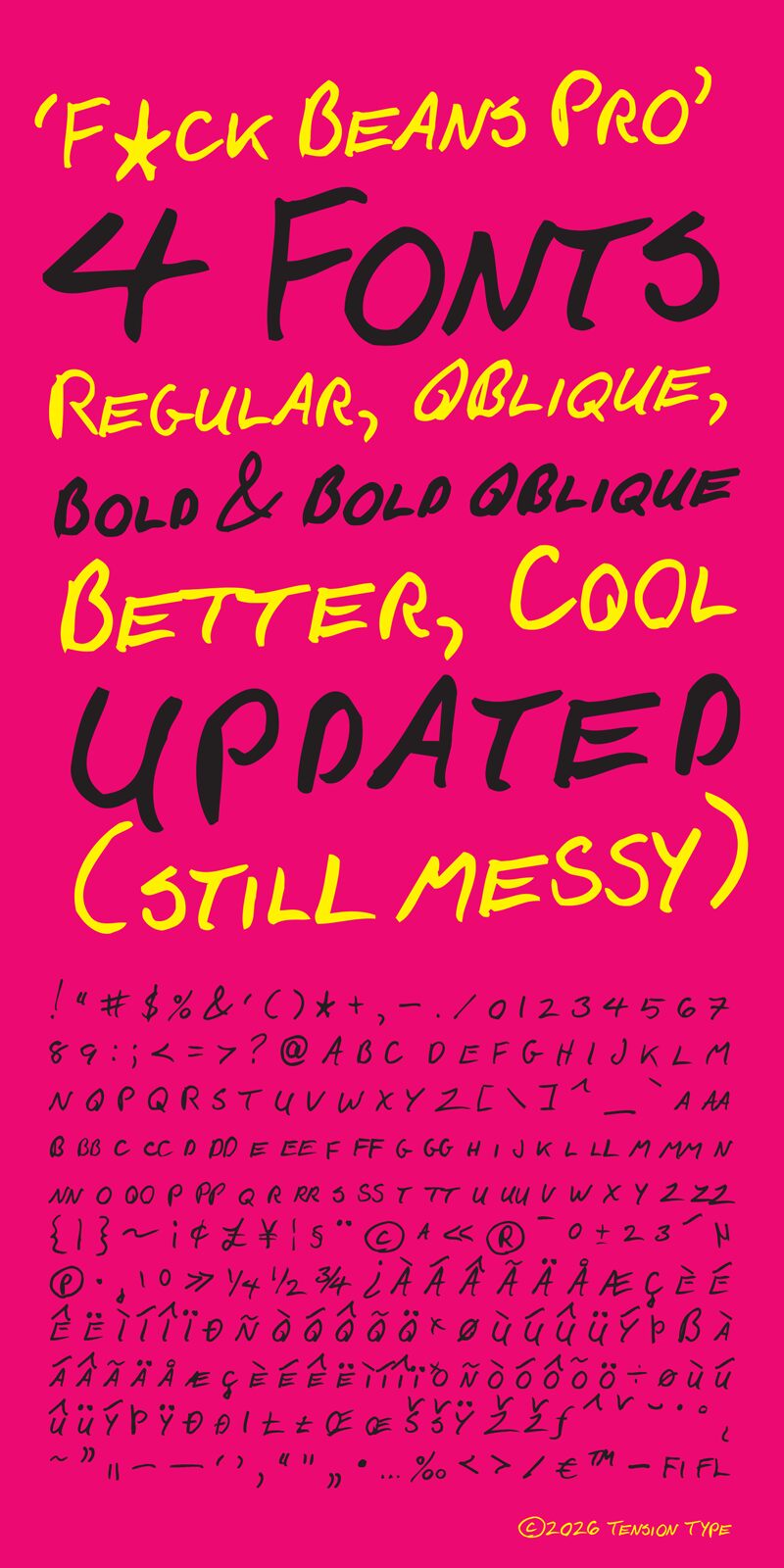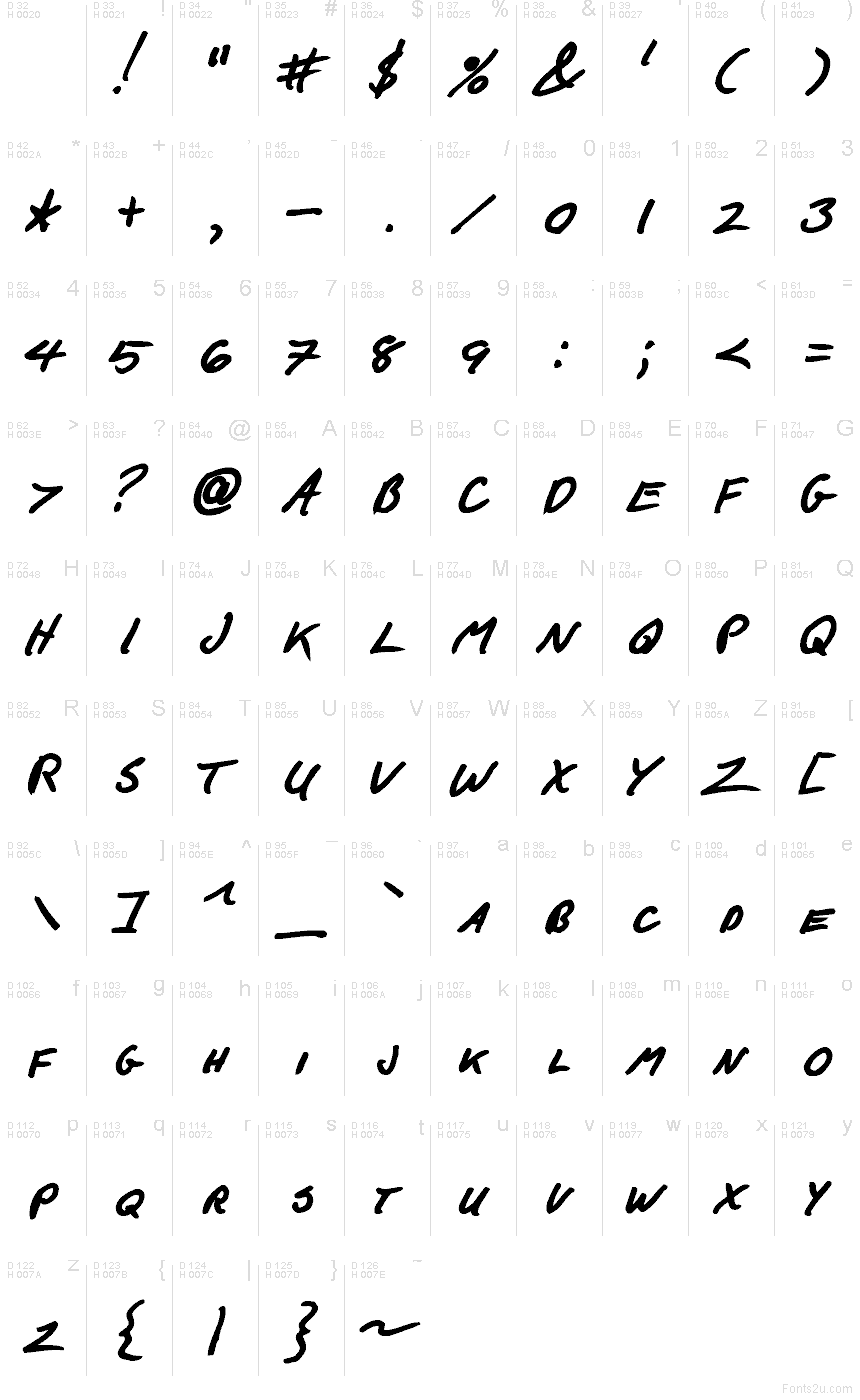
Fuck Beans Pro Bold Oblique est une police de caractères manuscrite penchée, idéale pour le titrage et disponible gratuitement. Elle capture l'énergie rapide d'une note griffonnée au marqueur pour lui donner une dimension d'en-tête percutante. Les lettres sont fortement inclinées et larges, mêlant des traits épais, des extrémités arrondies et des courbes douces : le résultat n'est pas soigné, il est brut, décontracté et délicieusement indiscipliné.
Elle est parfaite pour les slogans d'affiches, les visuels musicaux, le branding streetwear, les posts réseaux sociaux et les titres de couverture où l'on cherche une voix manuscrite qui a du poids. En tant que police gratuite, elle est aussi idéale pour des cartons de titre ou des noms sur des packagings courts, surtout si vous voulez cet aspect tracé à la va-vite sans sacrifier une silhouette grasse et impactante.
C'est l'écriture d'un vieil ami. Je l'ai créée il y a longtemps, alors que j'apprenais à utiliser Fontlab 5. Voici une version mise à jour. J'apprends encore.
F*ck Beans Pro
This is an old friend of mines handwriting. I created it a long time ago when I was learing how to use Fontlab 5. This is an update I have done. Still learning, but this version is definately an improvement.